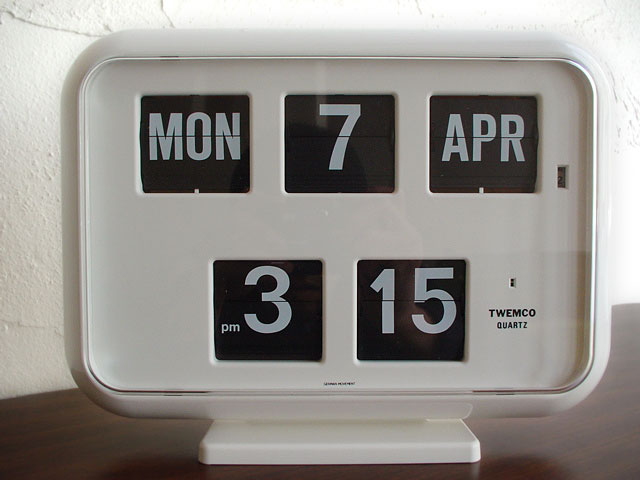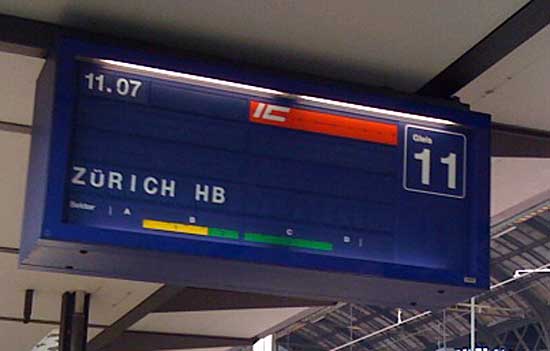
Klappbuchstabentafeln
Ich bin auf der Suche nach der Schriftart, die in Klappbuchstabentafeln und -uhren verwendet wird.
Ich weiß leider nicht, wie ich mich besser ausdrücken kann, weil ich mir nicht sicher bin, ob die so heißen; aber ich denk, Ihr wisst, was ich meine. Die Anzeigetafeln z.B. in Bahnhöfen oder Flughäfen mit den rotierenden, klappenden Buchstaben.
DIe haben immer eine spezielle Schriftart, die ich leider nicht kenne.
Ich habe leider nichts gutes im metz gefunden, nur diese Uhr hier 32358.jpg.
Wäre super, wenn Euch das reichen würde. Ansonsten würde ich nochmal verstärkt suchen. Vielleicht weiß ja auch jemand von Euch, wie die Anzeigetafeln eigentlich wirklich heißen.
Eine ähnliche Fragestellung hat es schon einmal hier gegeben. Es ist nicht davon auszugehen, daß diese Klappziffern grundsätzlich in der selben Schrift gefertigt werden. Die einzelnen Täfelchen werden ja wahrscheinlich im Siebdruck gefertigt, da kann man jede beliebige Schrift verwenden.
Danke für Deine Antwort! Den Artikel habe ich geselen. Mir ist klar, dass prinzipiell jede Schrift verwendet werden kann, es ging mir darum, ob Euch bekannt ist, ob in solchen Anzeigetafeln eine bestimmte Schrift klassischerweise verwendet wird.
Mein Anliegen ist, wenn ich das kurz erläutern darf, für ein Redesign eines Weblogs Grafiken in diesem Stil zu erzeugen. Momentan verwende ich dafür (nicht wegen der Ähnlichkeit zu echten Klapptafeln, eher wegen meiner Vorliebe und meinem persönlichen Geschmack) die Helvetica 63 Extended Medium.
Da Anzeigetafeln mit absoluter Sicherheit niemals so aussahen oder aussehen werden, hätte mich interessiert, was ich für realistischere Alternativen hätte, um die Thematik authentischer gestalten zu können.
Ein Schritt in die richtige Richtung könnte sein, mal nach Monospaced-Schriften zu suchen, also nach Schriften, wo alle Zeichen auf die gleiche Breite getrimmt sind. Das könnte ein verbindendes Element für mögliche Kandidaten sein, da die Tafeln ja immer eine Breite haben. Zu solchen Schriften solltest Du auch hier im Forum etwas finden.
Wenn ich das Beispiel von Bulu so anschaue ist das von monospaced aber weit enfernt …
Ja ne, das ist nicht monospaced, schon klar. Ich hadere auch noch mit mir, ob ich das so haben will. Ich finde das mit den unterschiedlich breiten Buchstaben gar nicht hässlich, da dies etwas mehr Dynamik in die Sache bringt, die ja eigentlich ziemlich starr ist.
Und auch wenn ich mir denken kann, dass Ihr die Helvetica für zu ausgelutscht haltet, finde ich ihren Einsatz hier eigentlich nicht schlecht.
Wie gesagt, mich hätte halt interessiert, ob Ihr da noch Anderes in petto habt, weil ich gern den Vergleich hätte.
… Ja ne, das ist nicht monospaced, schon klar. … Helvetica für zu ausgelutscht …
Das monospaced bezog sich auf Pachulke :D
Helvetica kann ich in deinem Beispiel keine entdecken :tutor:
Wie wäre es mit so etwas? Nicht monospaced, aber breite Einser:Bild 3.png[/attachment:34pldh1i]
FWIW, bei uns in der Schweiz ist das m.W. die Helvetica an den Bahnhöfen. Da steht das "I" dann halt ein bisschen alleine in der Gegend rum …
Beispielbildchen hier
da steht nicht wirklich "Postkutsche" Richtung Gotthardpass? Jessasmariandjosef…
Danke, ich werde das mit der Franklin Gothic mal probieren.
Ich muss mich korrigieren: Bei uns ist das eine *hust* modifizierte Helvetica Bold.